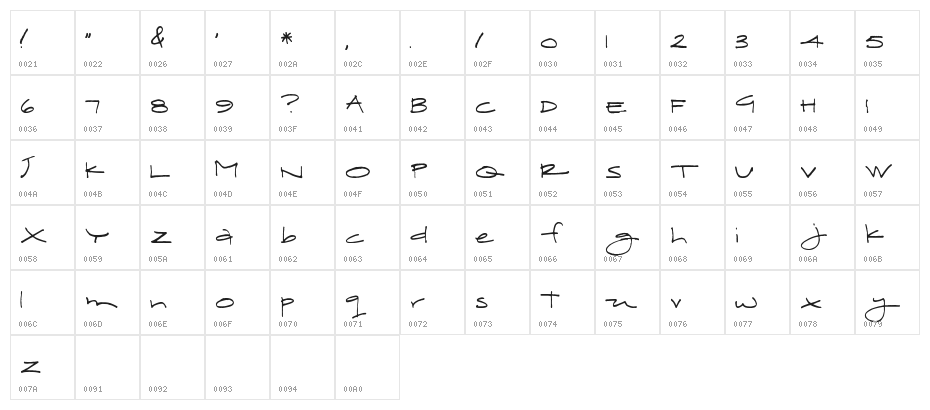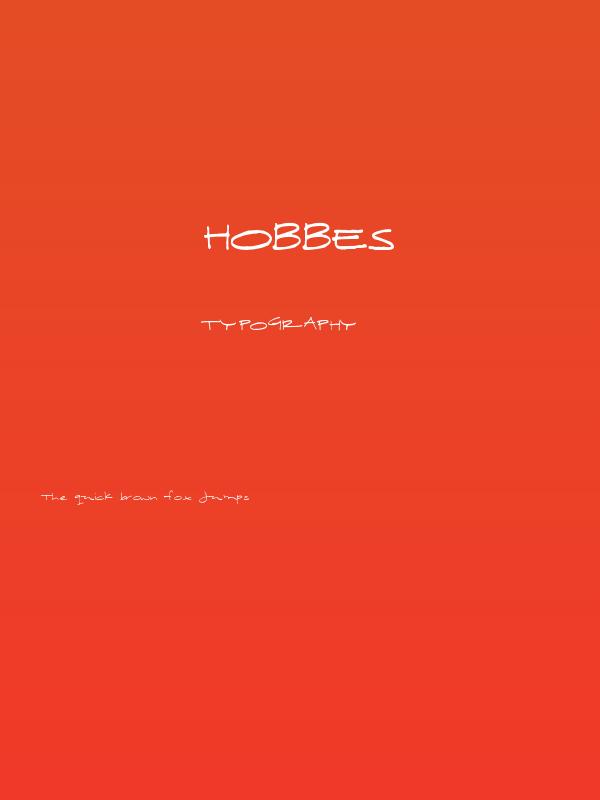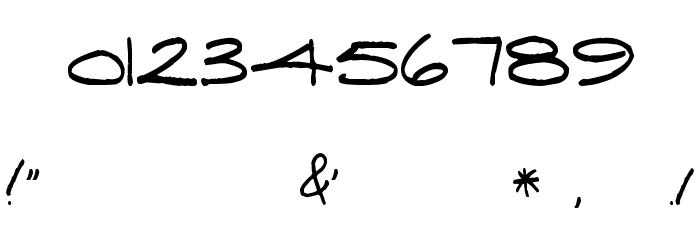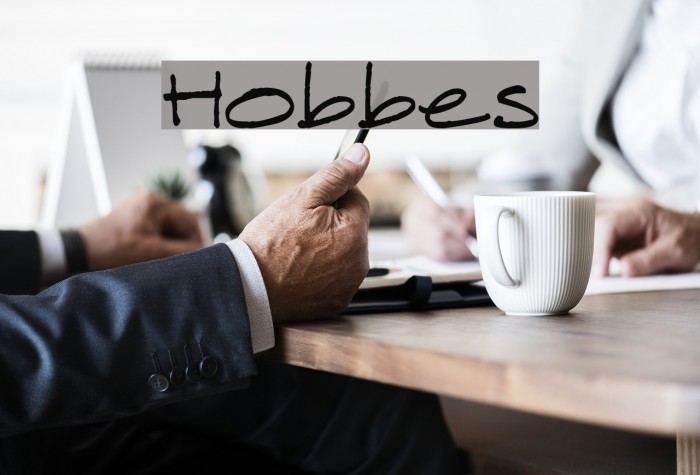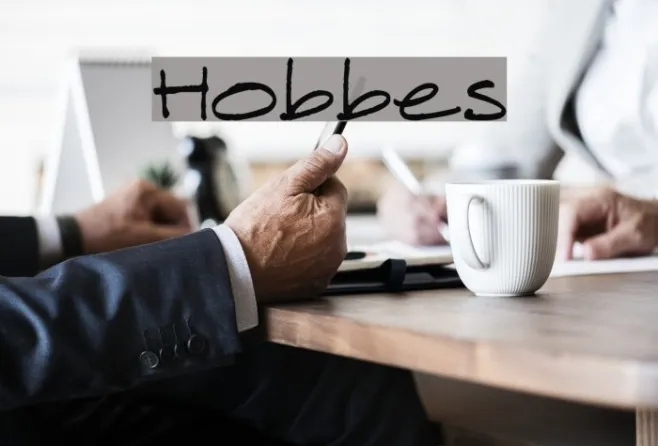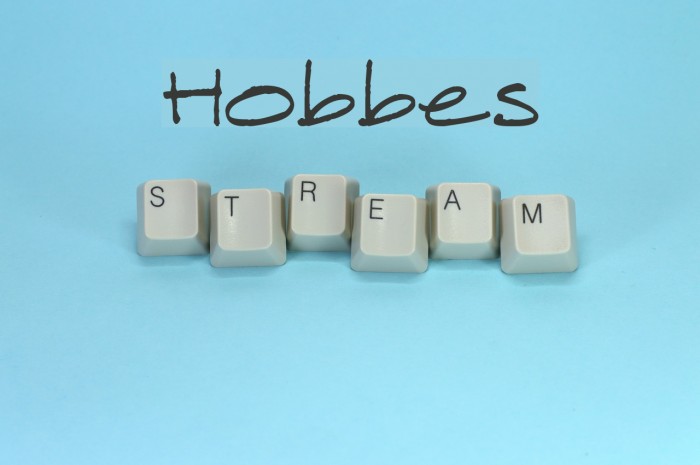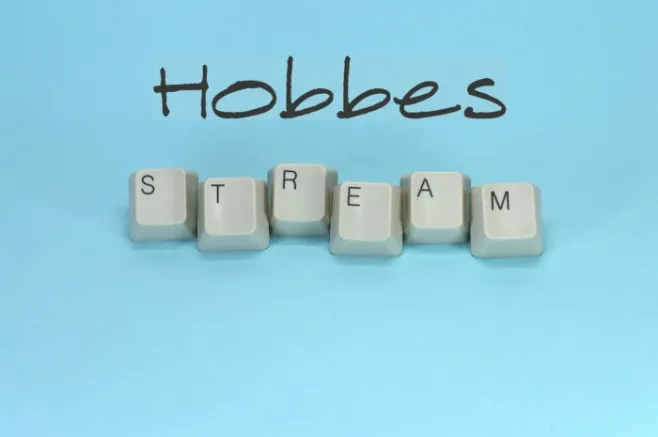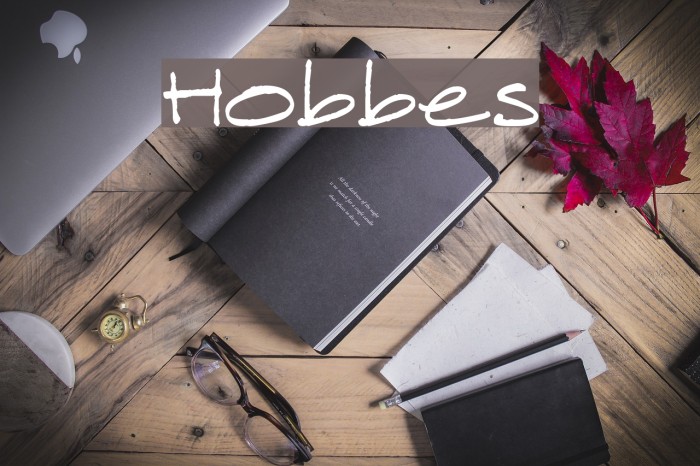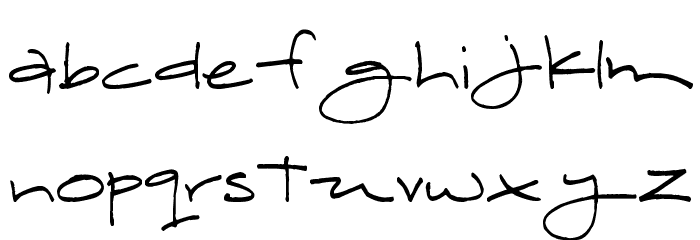
Hobbes Font
| Style général | Casual |
| Cas d'utilisation | Logos, Headlines, Informal Text |
| Projets proposés | Ideal for greeting cards, personal branding, casual invitations, and playful marketing materials. |